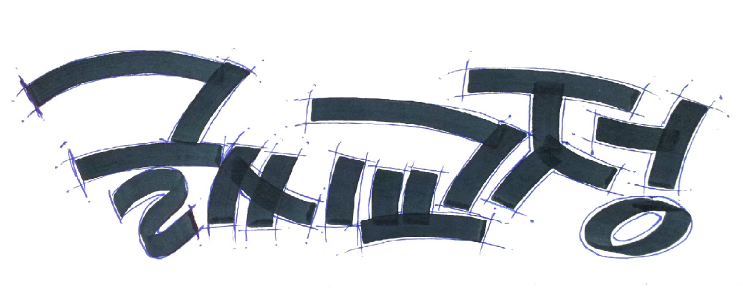
안녕하세요?
다년간 글씨교정 강의를 했던 강의 교재 내용을 공유해 드리고자 본 블로그를 개설하오니,
글씨 때문에 고민하셨던 분들에게 많은 도움이 되기를 기대합니다.□ 학습목표
바른 글씨 체본의 습자를 뛰어 넘어, 선의 각도, 길이, 방향, 위치에 변화를 주어 자기만의 조화롭고 균형미 넘치는 글씨를 쓰자 !!!
본 블로그에서는 아래의 필봉 경사응용체를 습득하는 것을 목표로 합니다.
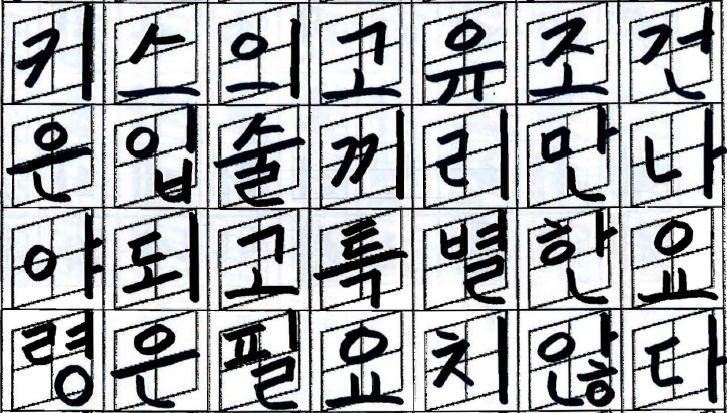
□ 습득요령○ 집필법(펜잡는 요령)
- 영역을 넓히자 ! (동그라미를 유지)
- 힘을 빼고 엄지로 중지를 눌러쓰지 말자 ! (손가락이 아프지 않게...)
- 종이와 펜의 각도는 45도정도 에서 자기만의 방법을 찾자 !
○ 바른자세(앉는 자세) / 습관교정
- 허리를 펴고
- 공책은 반듯이
○ 필법(한글의 원리)을 깨우치자 !
- 자획의 순서 및 요령을 터득하자!!!
- 글자의 짜임새(구성형태)에 대한 이해
- 효율적인 자획의 조립
- 획의 변화 및 단순화(판본고체 → 경사체 → 경사응용체 → 정자체)
○ 규칙과 공간배열, 상호조화의 디자인적 감각을 키우자 !
- 정확한 비율(간격, 형태, 각도, 길이, 방향, 위치) 습득과 응용
- 분석 없는 단순 습자는 무의미 하나 분석을 통한 모방과 연습은 필수 !
- 규칙과 형태를 내 것으로 논리적으로 소화시키자 !
○ 천천히 꾸준하고 꼼꼼하게 연습하자 ! (20~30분/일)
- 성격의 완급조절
- 노력의 결실
- 한 글자를 마무리하고 다음 자를 쓰자 !!!
- 복잡한 획보다 단순한 획부터, 긴 획보다는 짧은 획부터 체득하자 !!!